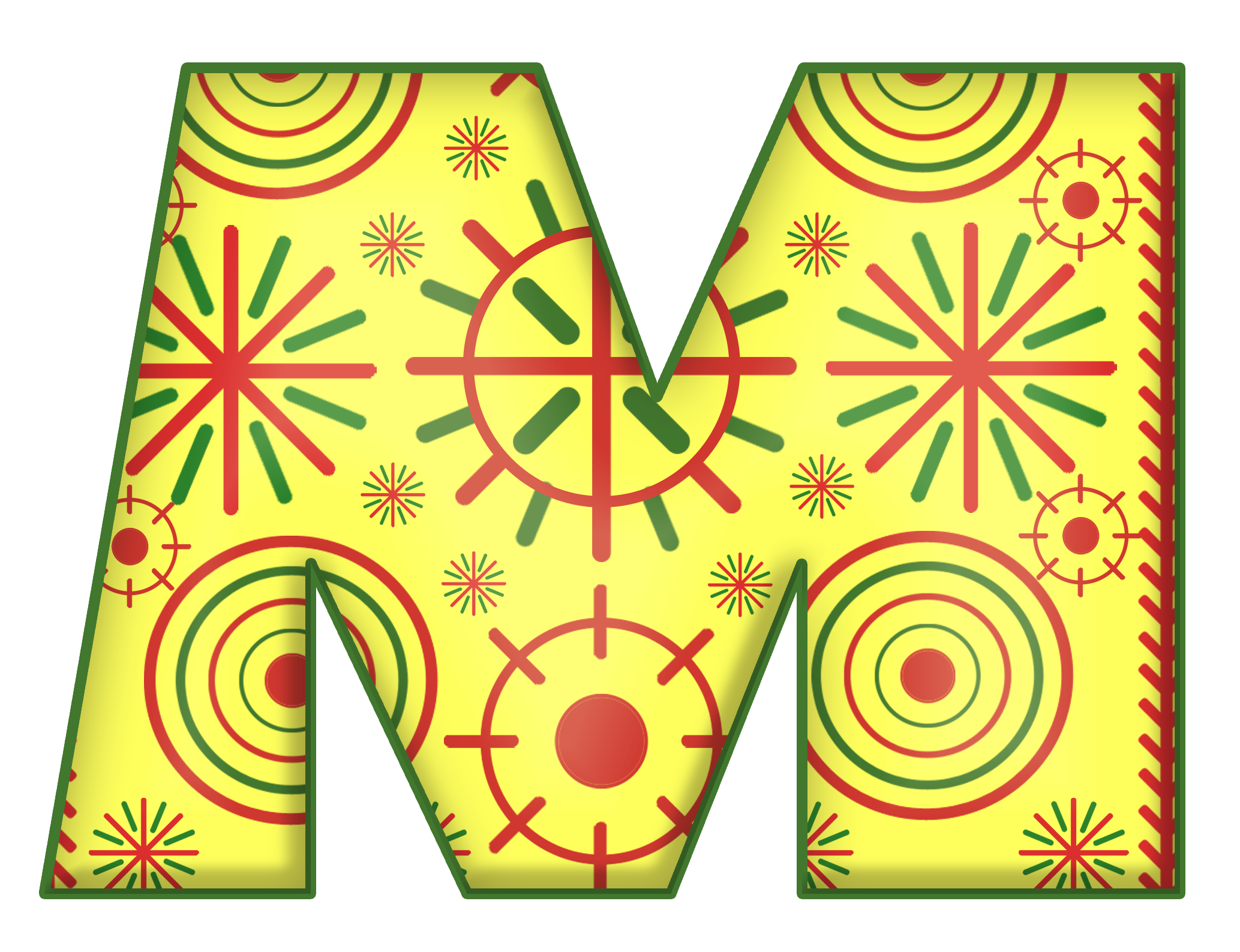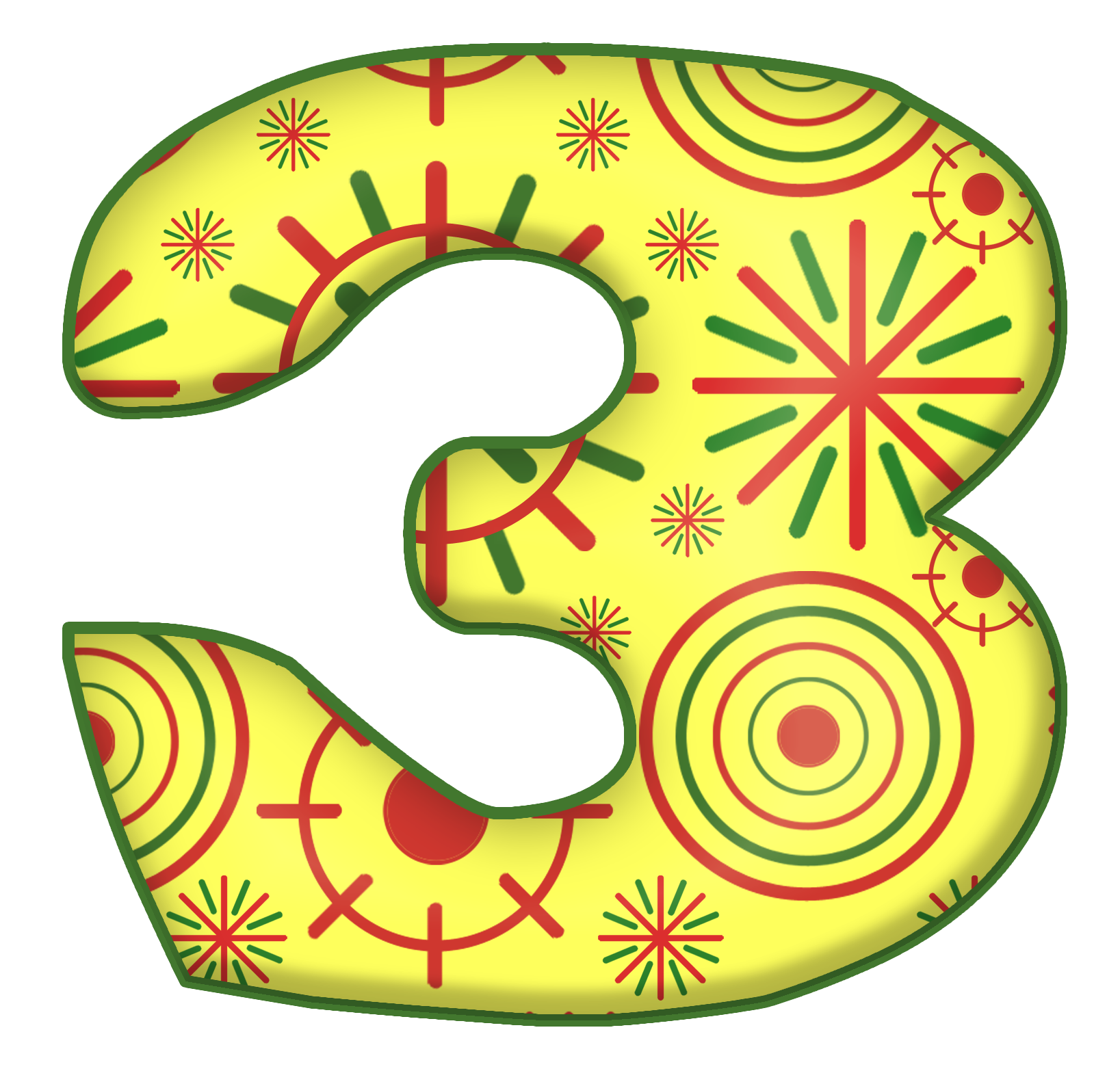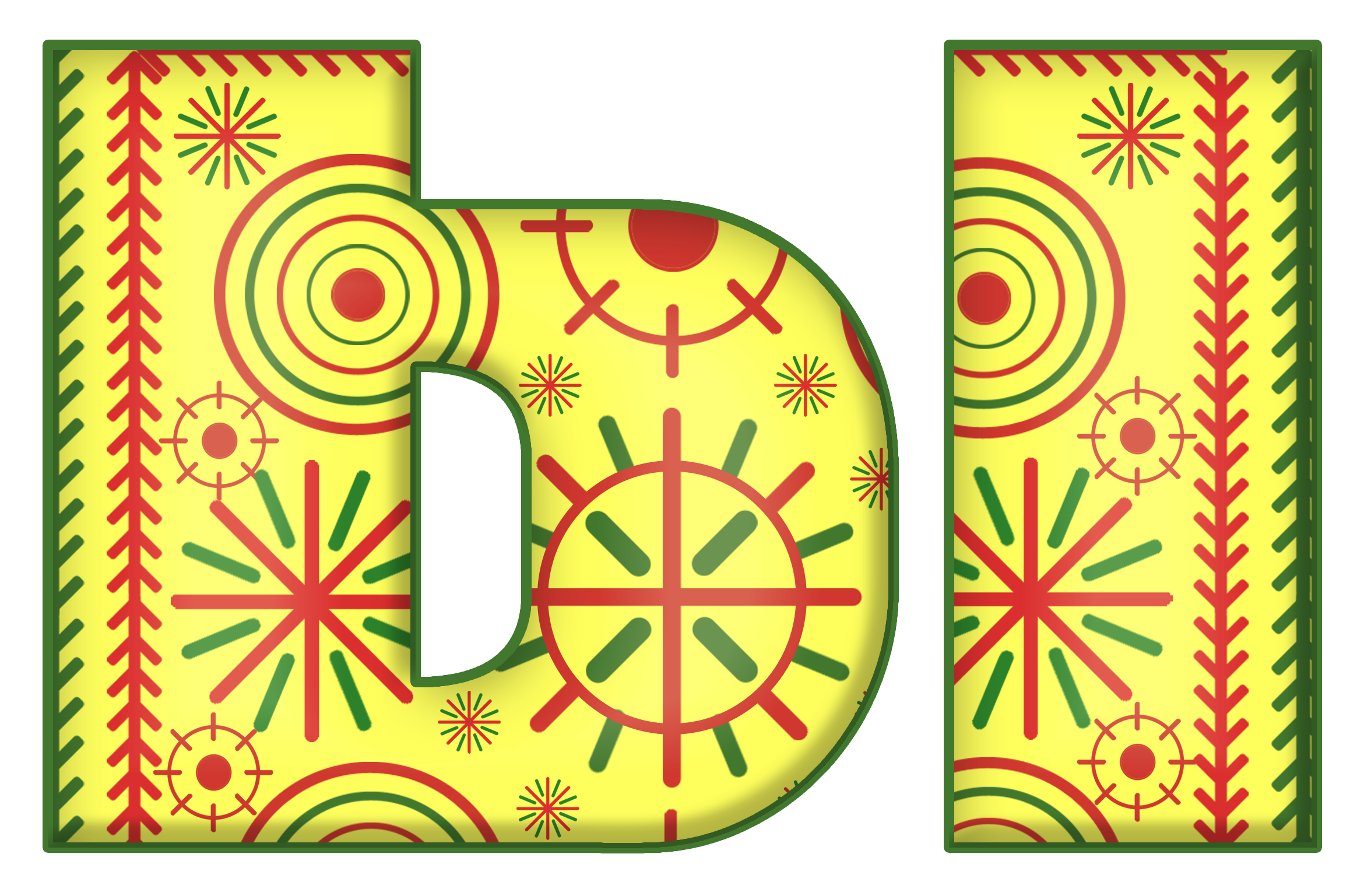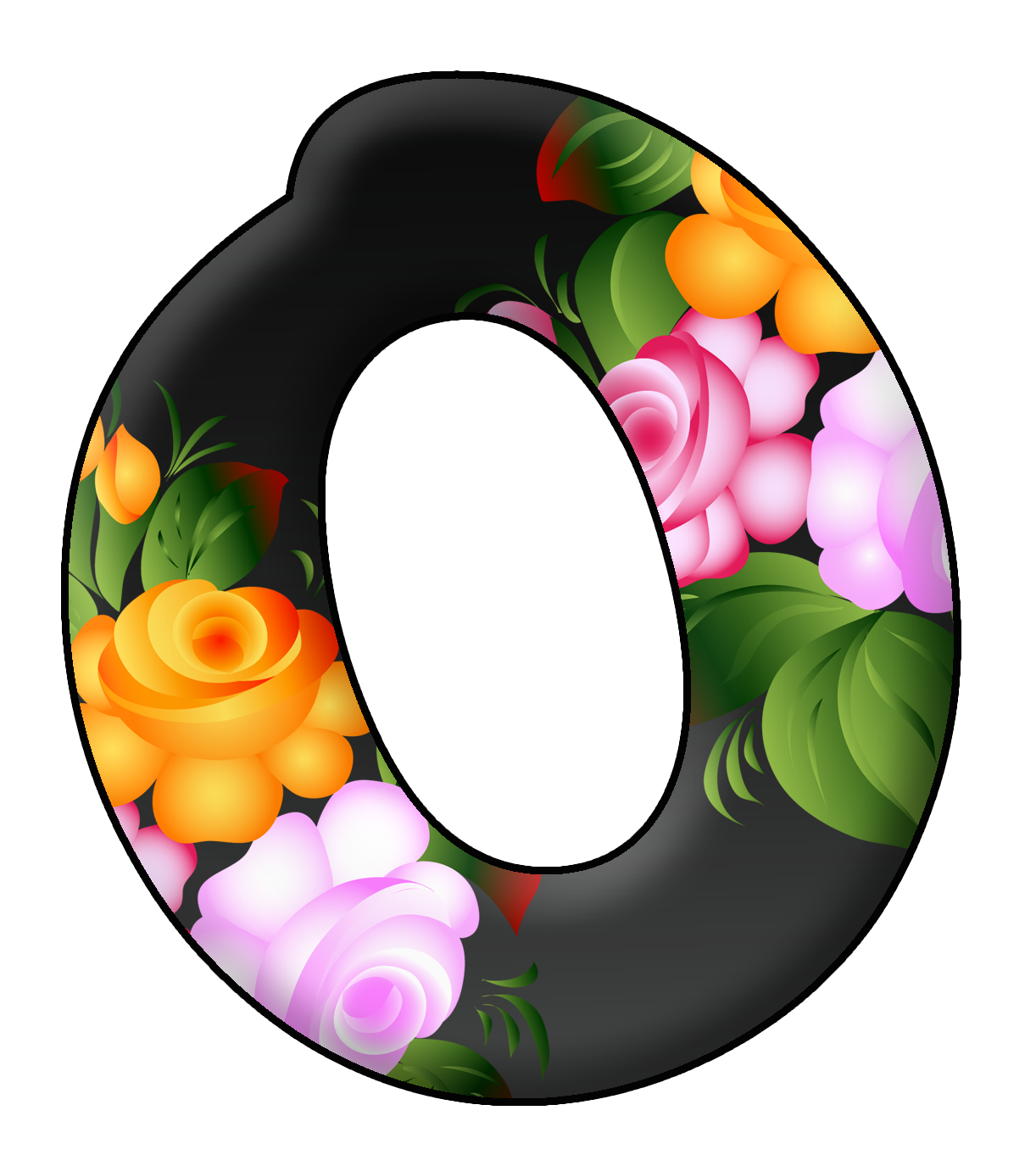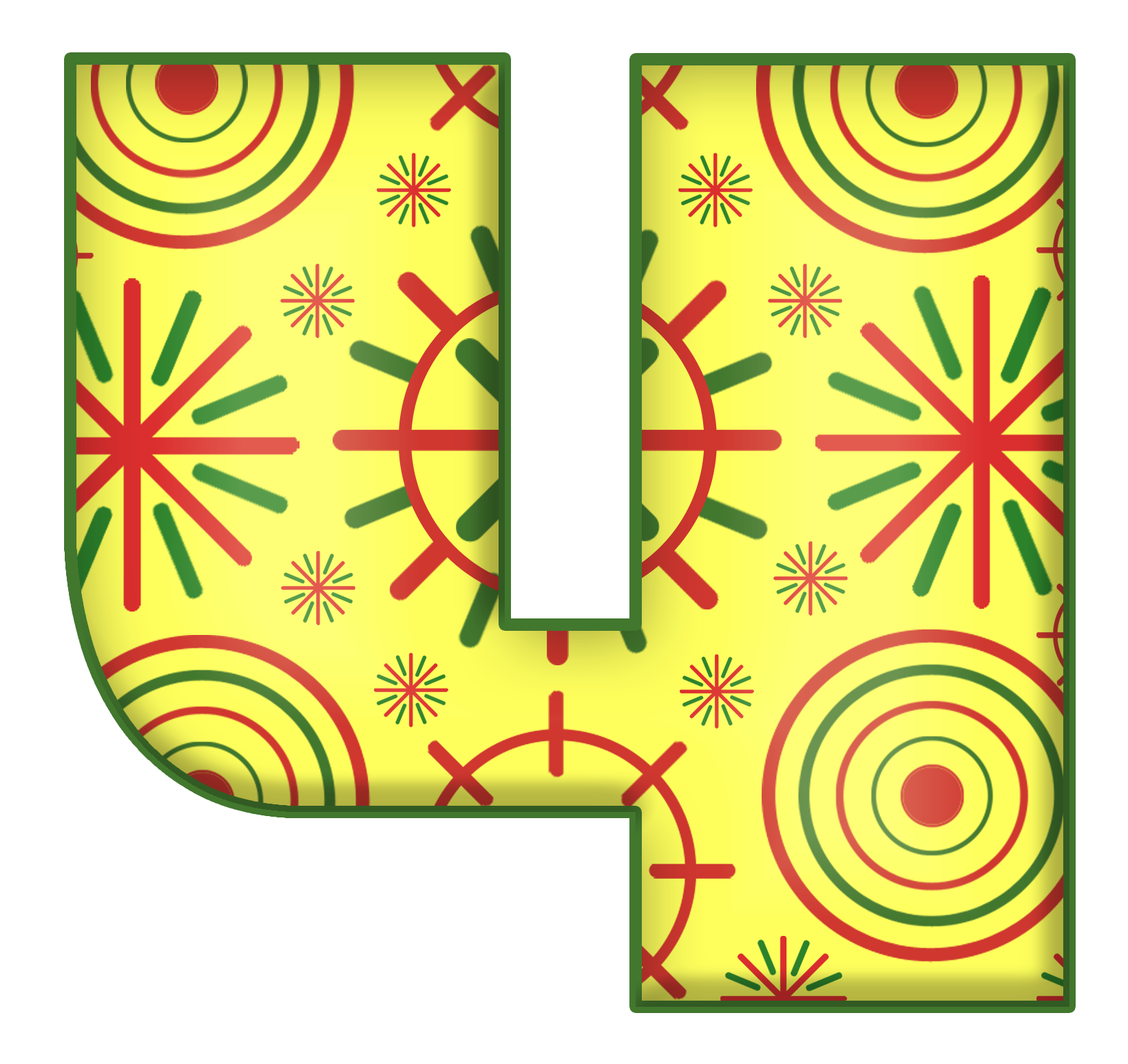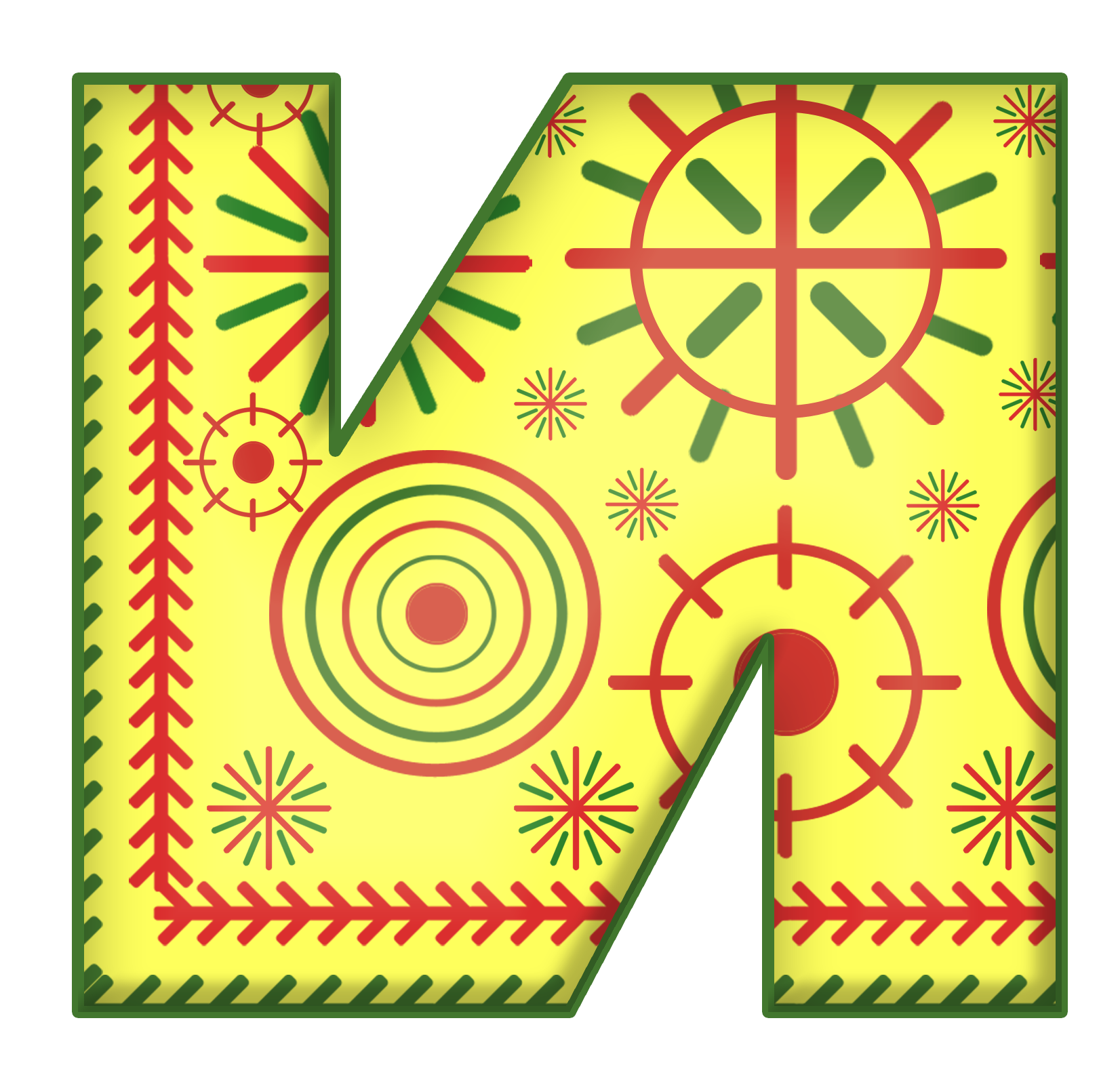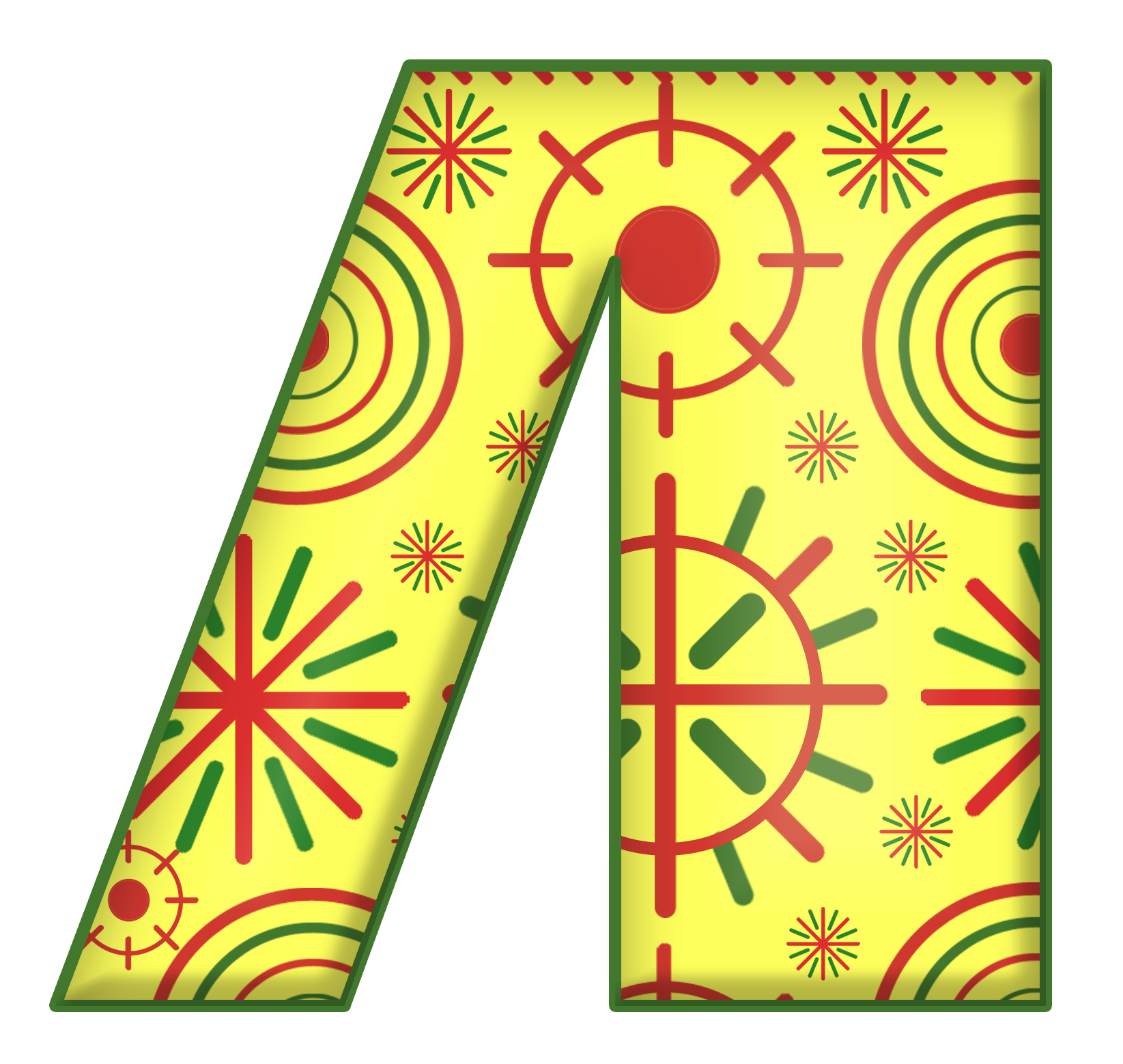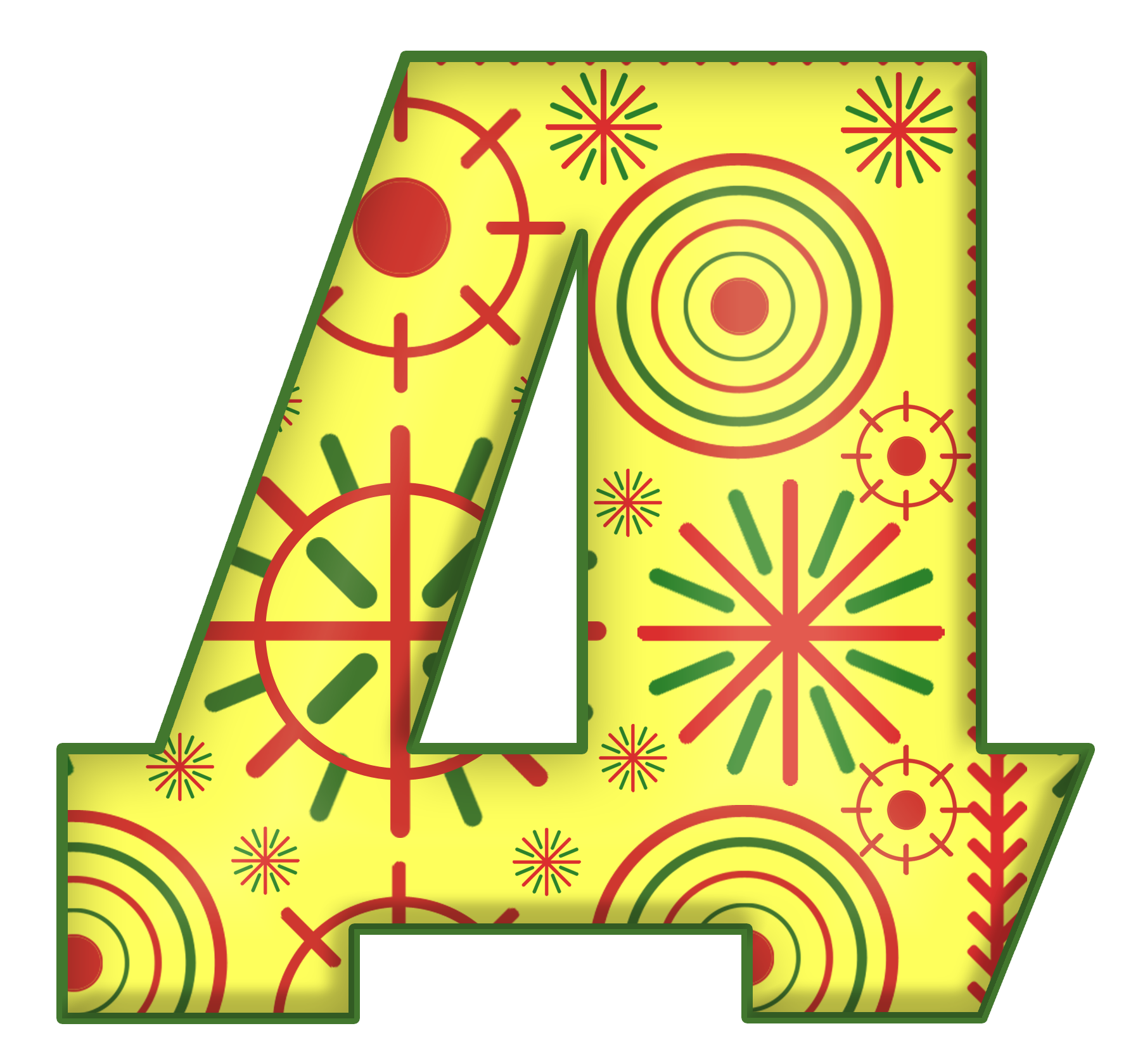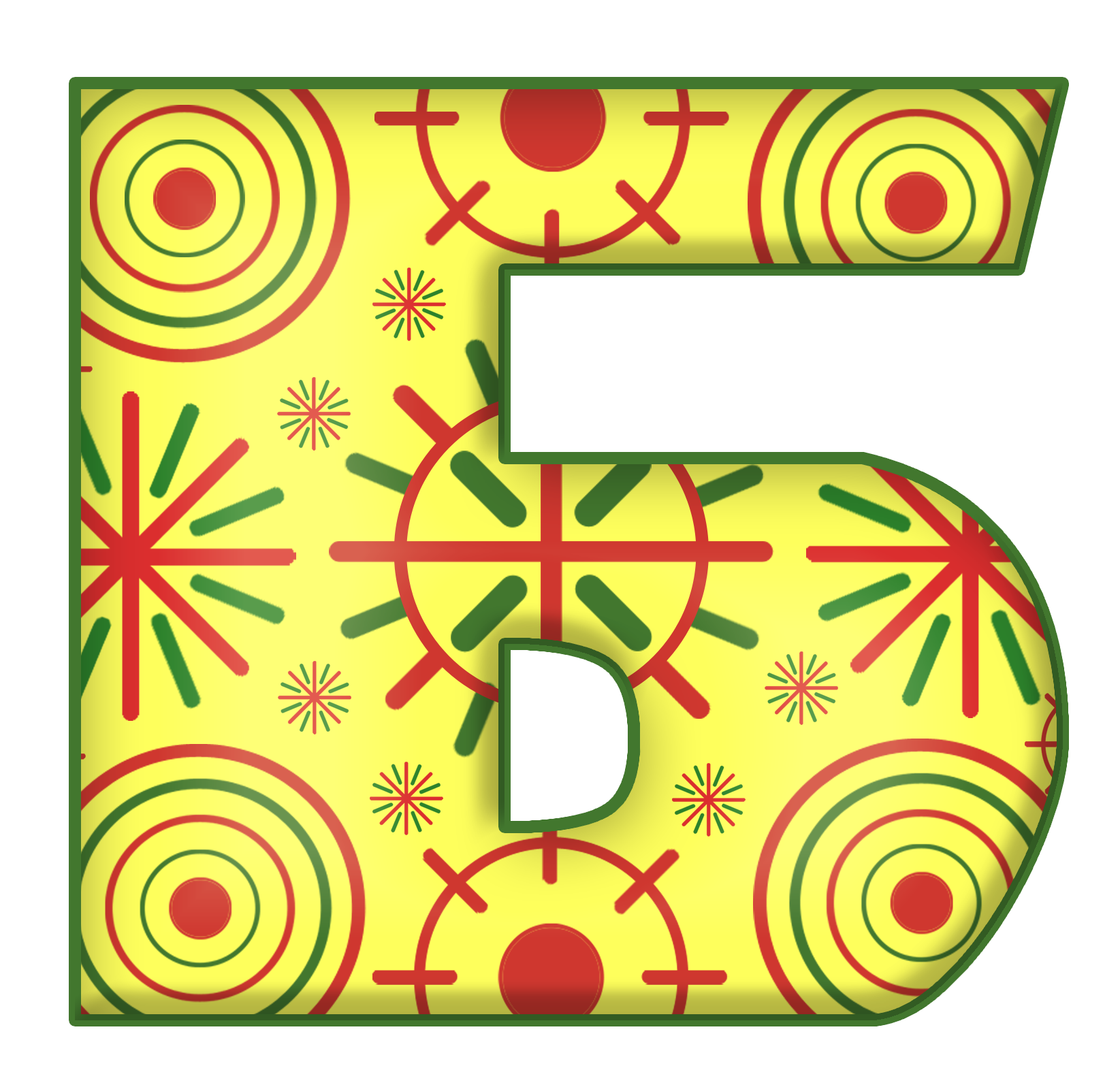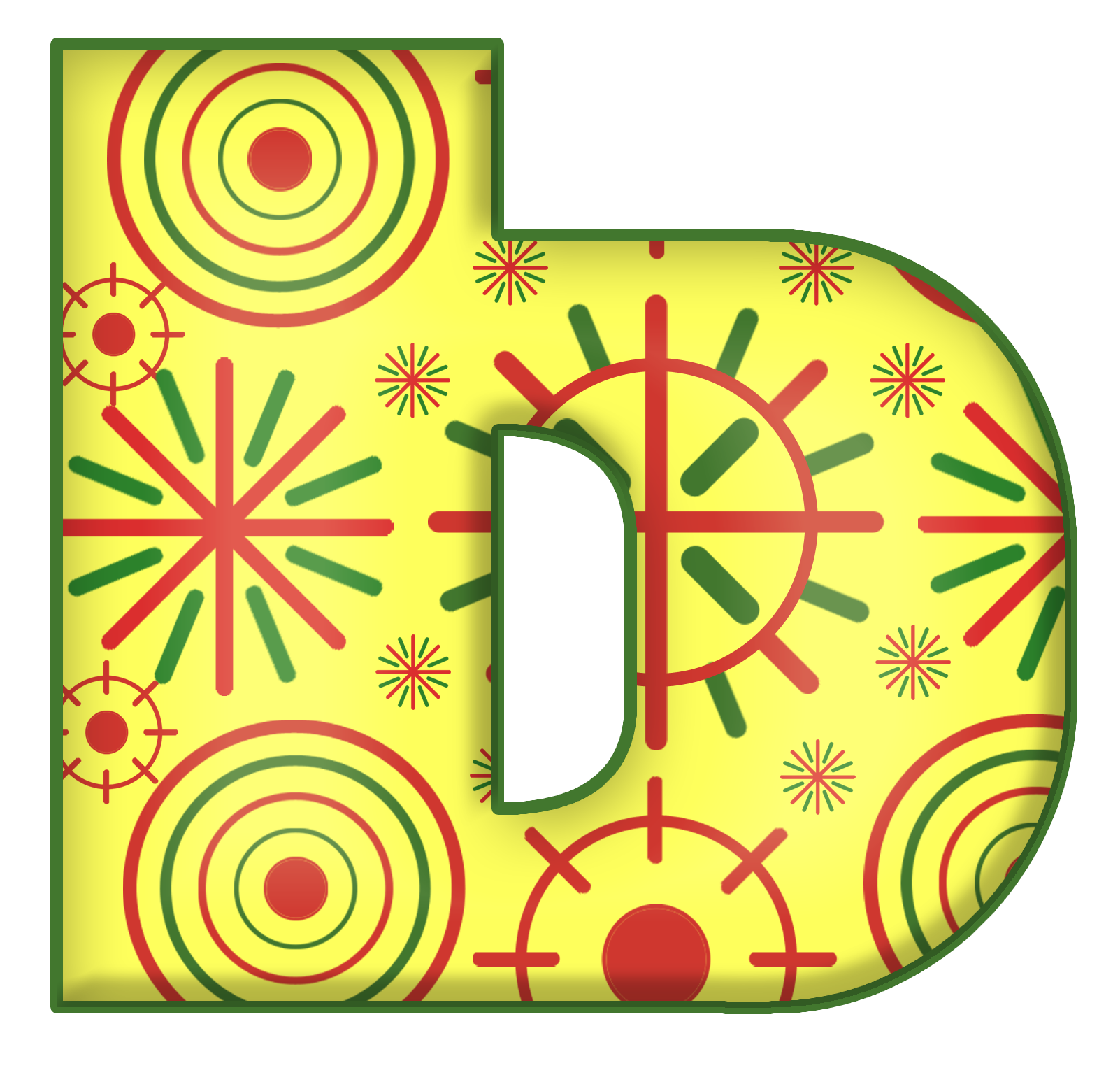
Шрифты в стиле народных промыслов (4)
ГЖЕЛЬ
Шрифты в стиле народных промыслов (4)ГОРОДЕЦКАЯ РОСПИСЬ
Шрифты в стиле народных промыслов (4)ЖОСТОВСКАЯ РОСПИСЬ
Шрифты в стиле народных промыслов (4)В СТИЛЕ �ИЛИМОНОВСКОЙ �ГРУШКИ
Шрифты в стиле народных промыслов (4)"КНЯЖЕСКАЯ ВЯЗЬ" НА ЗАКУСКУ
Шрифты в стиле народных промыслов (4)БЕРЕСТА
Ох как я люблю Жостовскую роспись, для меня, красивее ничего быть не может.Спасибо.Тоже не знаю пока зачем, но не могла устоять перед красотой.